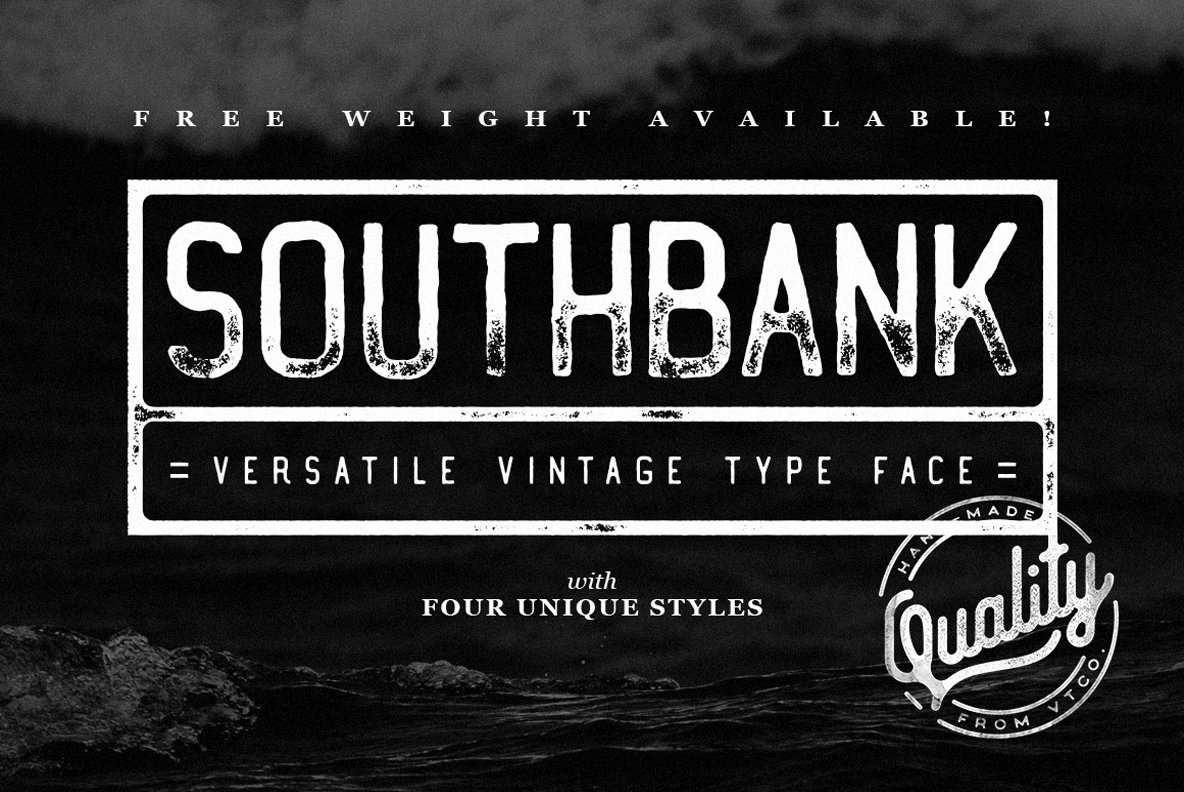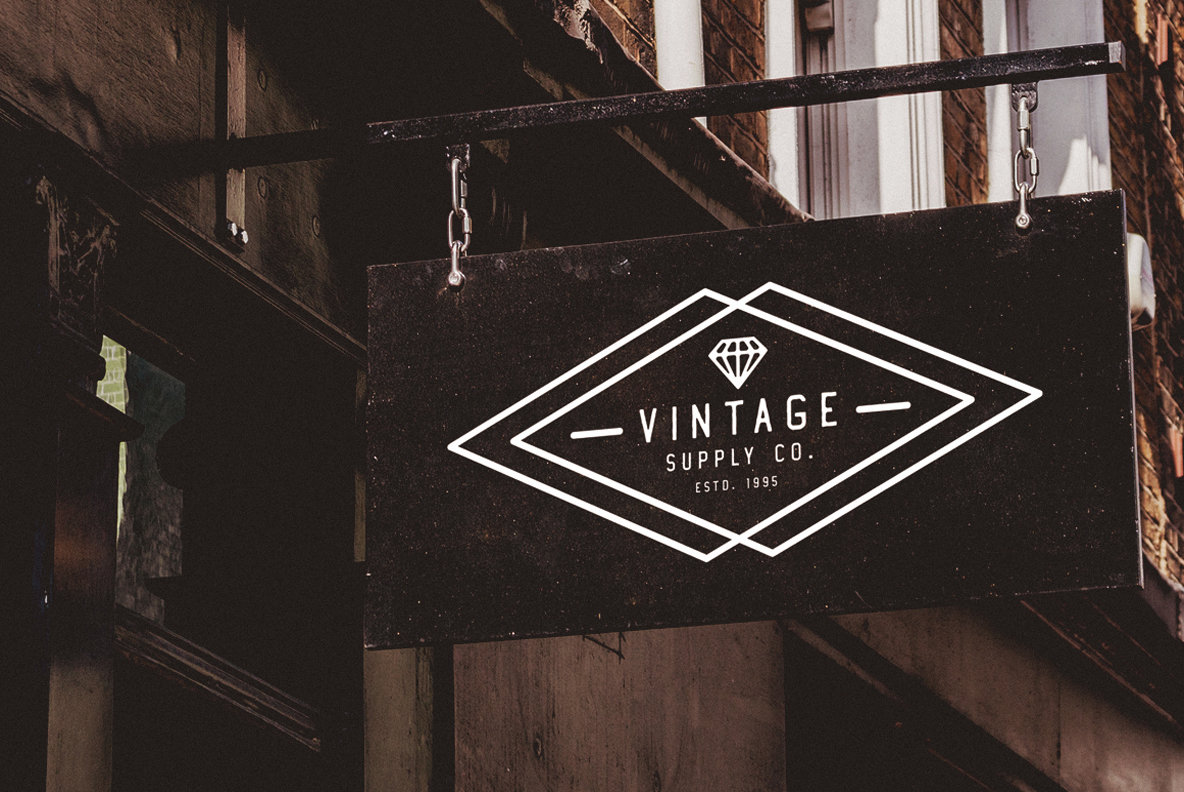
Font family: Southbank LT
Font subfamily identification: Regular
Unique identifier: VintageTypeCompany Southbank LT 2016
Full font name: Southbank LT
Postscript font name: SouthbankLT
Manufacturer name: Vintage Type Company
Designer: Sean Coady
Southbank LT
Винтаж Тип Co
Винтаж Тип Ко [Шон Коди]
Графический дизайнер из Саммерсайда и/или Шарлоттауна, Остров Принца Эдуарда, Канада, который работал сначала в Эдмонтоне, Альберта, затем в Монктоне, Нью-Брансуик, затем в Торонто и, наконец, в Галифаксе, Новая Шотландия.
Он руководит SRC Designs и в 2015 году основал Vintage Type Co (не путать с Vintage Type Сьюзен Таунсенд, компанией, основанной в 1990-х). Создатель семейства бесплатных шрифтов без заголовков Муниципальный (2013 г.) и шрифта Fruit Sale с ручной печатью (2013 г.).В 2014 году он создал Shifty Sailor (стимулированный шрифт), Hofmann (психоделический шрифт), Kalopsia Slab (сжатое семейство шрифтов с засечками в стиле декоративно-прикладного искусства). Один вес бесплатный, остальные можно купить здесь. Он также создал бесплатные значки пользовательского интерфейса в 2014 году.
Шрифты 2015 года: Jackal Display, Anaheim Gothic, Alehouse (винтажный связанный шрифт), Dorchester Display (винтажный викторианский шрифт), Huxley (кистевой шрифт), Drone Ranger (восьмиугольный антиутопический шрифт) , Authentico (винтажный плакатный шрифт в восьми стилях), Firefly (бесплатный плакатный шрифт), Highbinder (стертый винтажный шрифт), Adventurous Script (акварельная кисть), Nomad Icon Font, Arctic Express (ручная работа).
Гарнитуры 2016 года: VTC Numeric (бесплатно), Grindstone (винтаж), Grindstone Script, Grindstone Sans, Midnight Owl, Southbank (бесплатно), Planet Rouge, Life Is Jazz Script, Mystery Tour (+Sans) (многослойная Americana или цирковой шрифт), Sugar Boats, Navy Queen (хороший бесплатный шрифт, вдохновленный винтажными морскими плакатами).
Гарнитуры 2017 года: Virgo Antique, Virgo Display, PressBox (эмуляция высокой печати и Americana), Merchant Street Sans (восемь наращиваемых шрифтов), Old Spirits (стимулированный викторианский стиль), Prizefighter (арт-деко без шрифтов), Andre's Diner, Artisans Script ( фирменный сценарий), Milton Grotesque (бесплатный американский гротеск с заглавными буквами), Queen Street (многоуровневая семья).
Гарнитуры 2018 года: Grindhaus Sans (геометрический), Drone Ranger Pro (восьмиугольный).
Гарнитуры 2019 года: VTC Bloke (возрождение египетского расширенного шрифта Miller&Richard, широкого шрифта, напоминающего египетские типы дерева), VTC Horoscope.
Гарнитуры 2020 года: VTC Elmwood (модернизированное семейство шрифтов для черных букв), Fellbaum Grotesk, VTC Fellbaum Grotesk.
Гарнитуры с 2021 года: Chocolate Chiped (семейство сжатых гарнитур, имитирующих ксилографию).